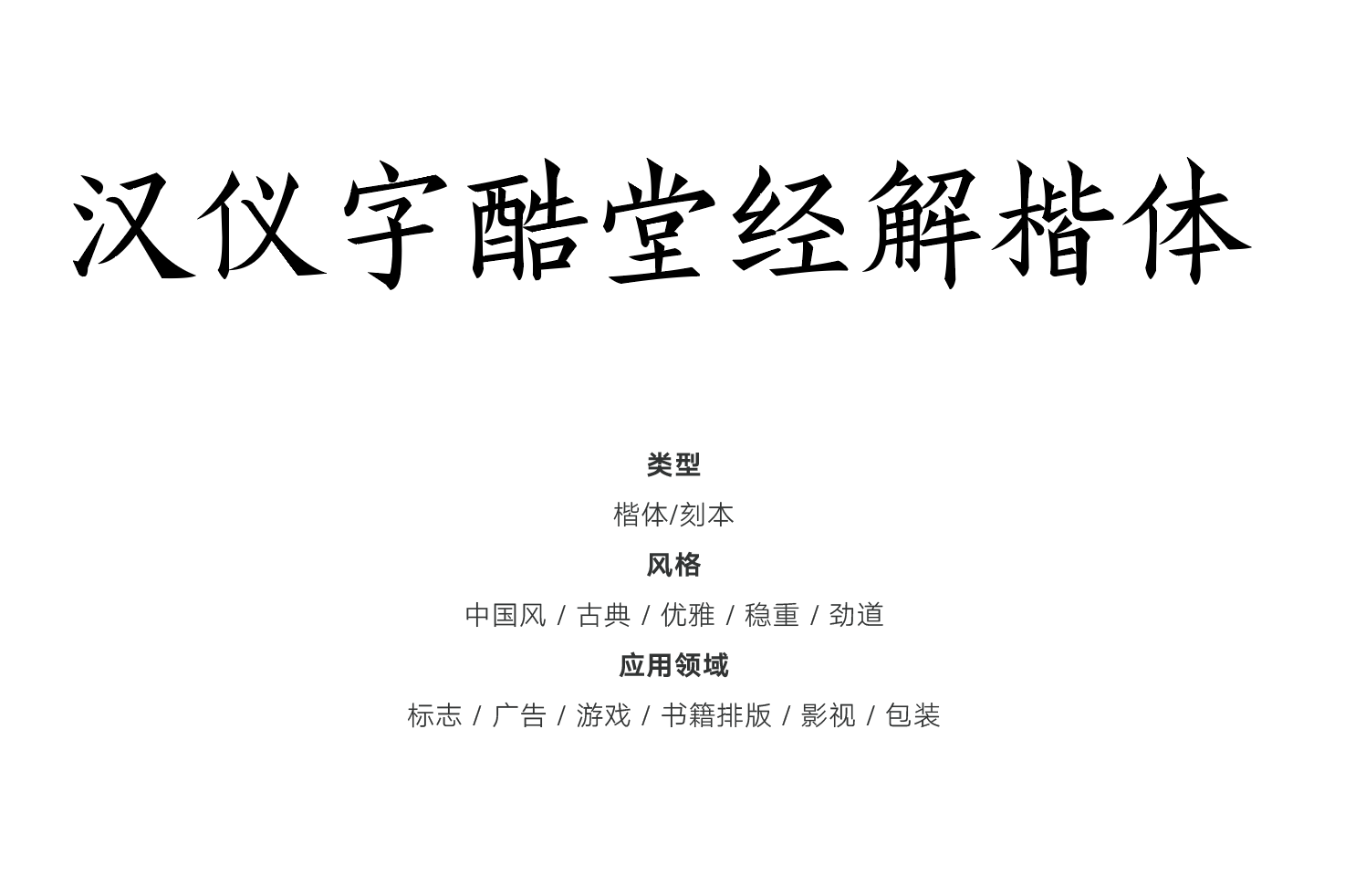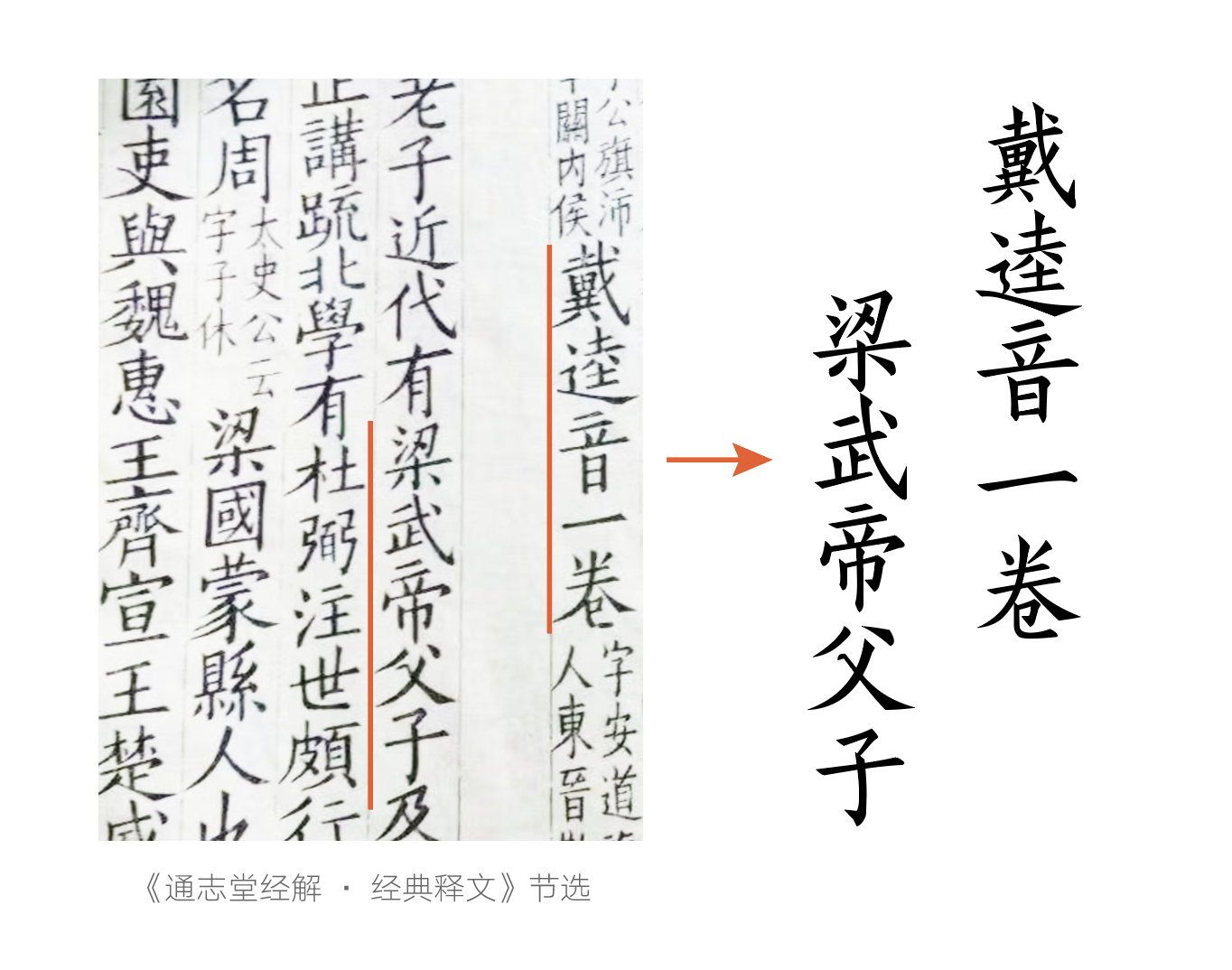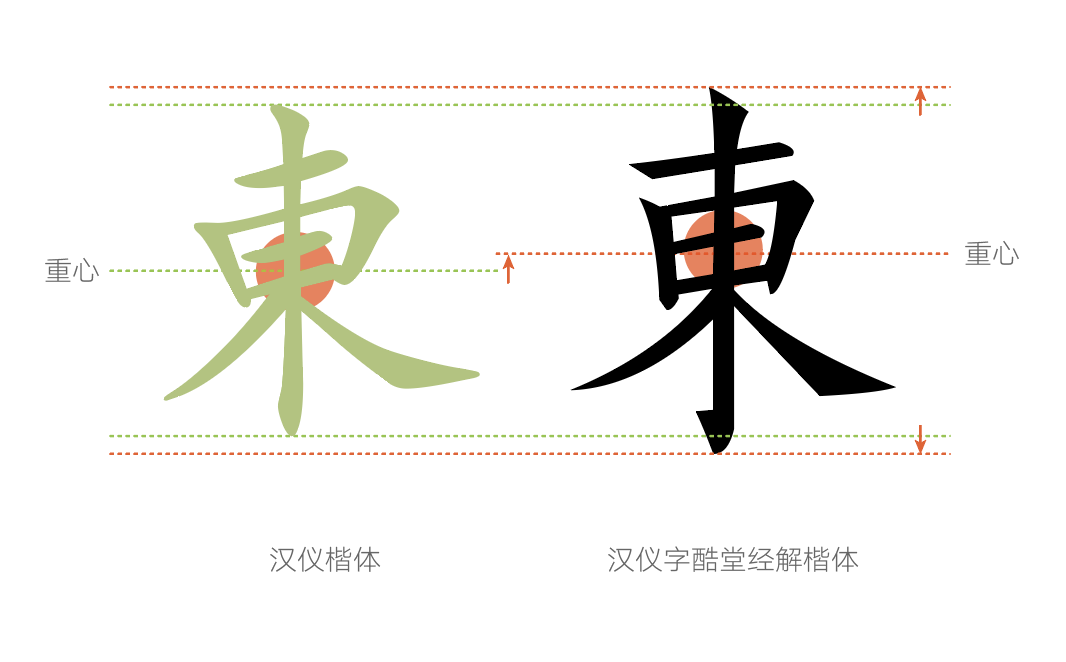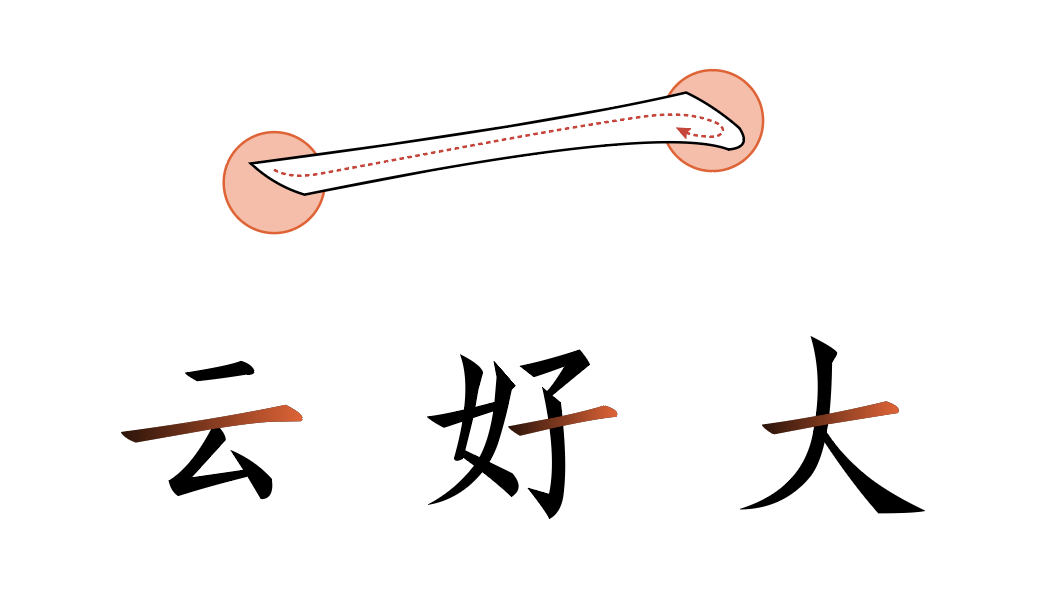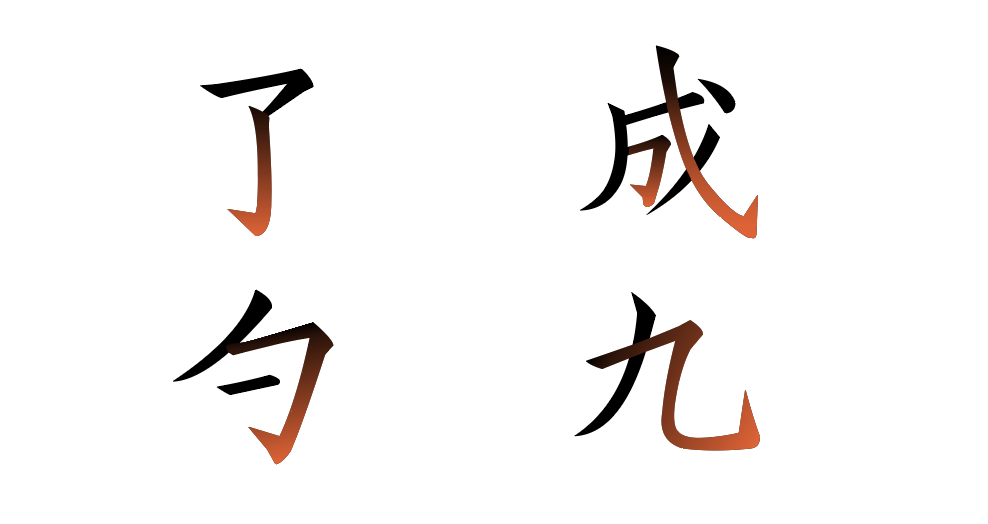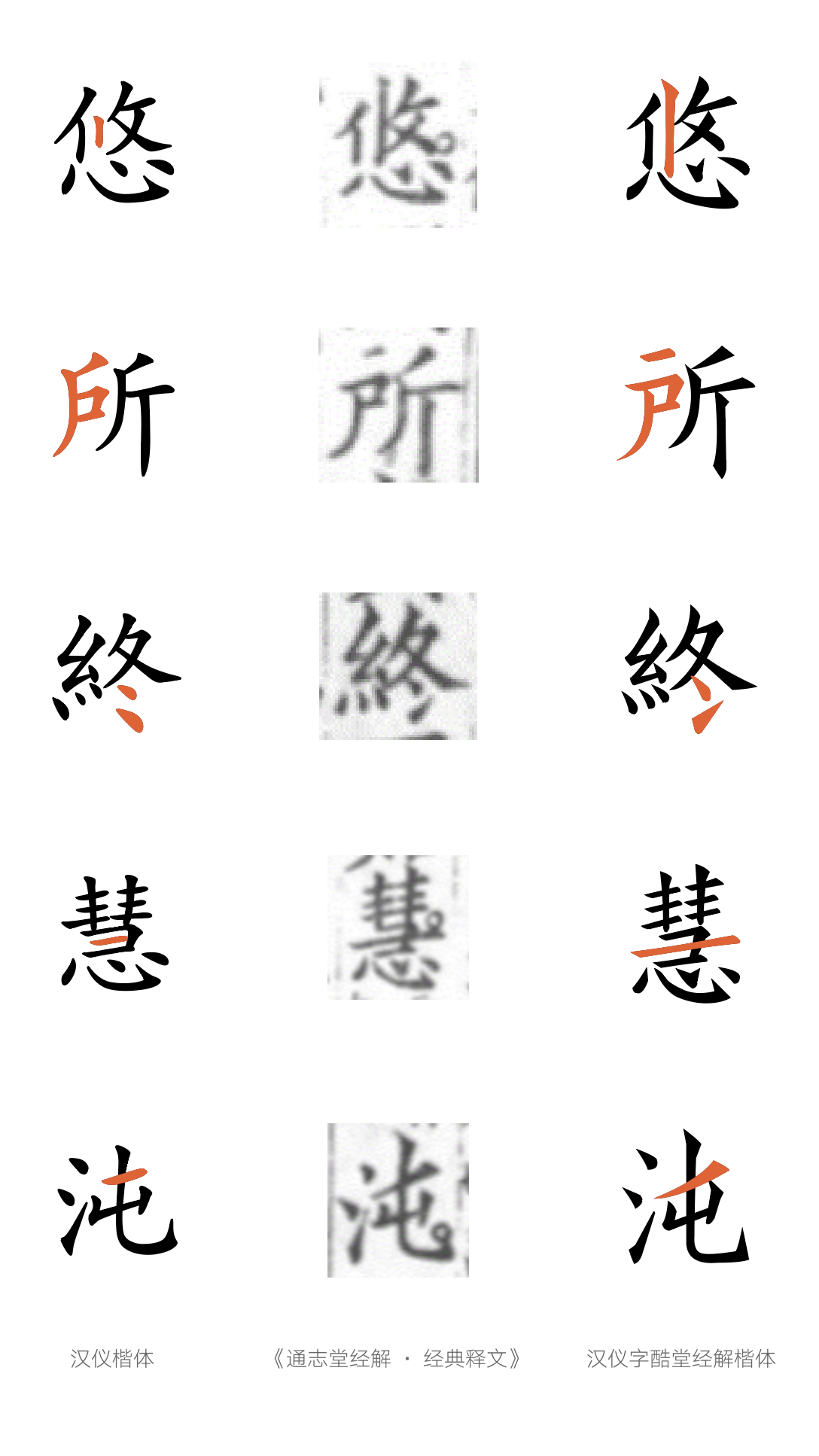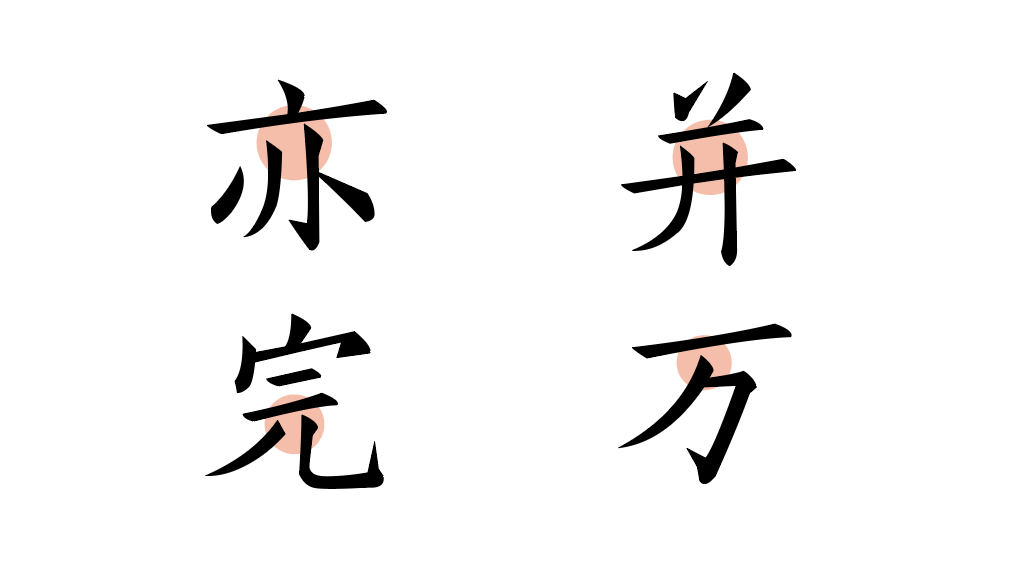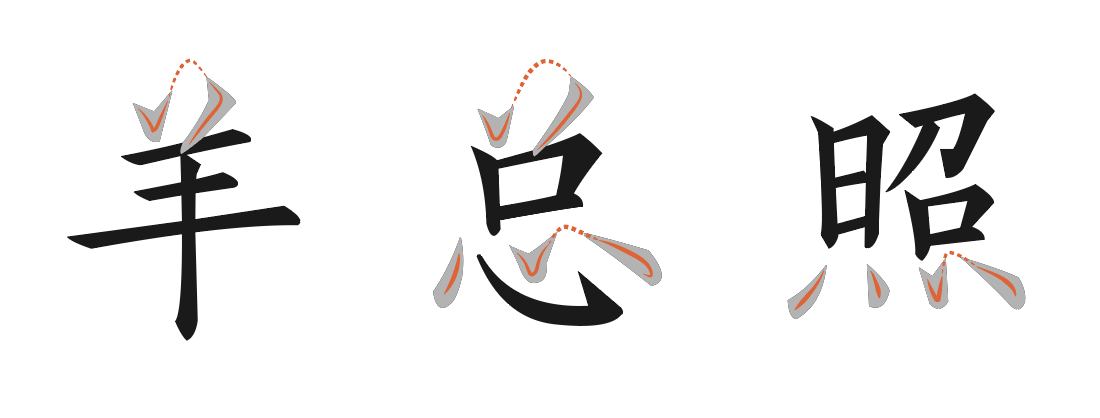
漢儀字酷堂經(jīng)解楷體
字體來(lái)源
漢儀字酷堂經(jīng)解楷體來(lái)源于古籍《通志堂經(jīng)解·經(jīng)典釋文》一書(shū)(清康熙年間,陸德明撰),字體有歐體楷書(shū)風(fēng)格,嚴(yán)謹(jǐn)工整、平正峭勁。
漢儀字酷堂經(jīng)解楷體作為一款復(fù)刻字體,保持了原刻本筆畫(huà)堅(jiān)挺,骨氣內(nèi)含,既不過(guò)分瘦勁,又不過(guò)分豐滿的風(fēng)格特點(diǎn),在貼近刻本原貌的同時(shí),還十分注重字符的易讀性和辨識(shí)性。
字形修長(zhǎng),嚴(yán)謹(jǐn)工整
相對(duì)于常見(jiàn)楷體(漢儀楷體)而言,漢儀字酷堂經(jīng)解楷體在縱向上的拉長(zhǎng)延伸使得字體在縱勢(shì)上顯得疏朗、修長(zhǎng)、剛勁、挺拔。
筆畫(huà)出鋒勁健,遒勁有力
漢儀字酷堂經(jīng)解楷體的筆畫(huà)方圓兼施,以方為主。橫畫(huà)左低右高,露鋒入筆,筆鋒尖銳,中部飽滿,收筆內(nèi)斂,形成一個(gè)圓弧頭。
漢儀字酷堂經(jīng)解楷體的點(diǎn)畫(huà)飽滿,活潑靈巧,筆勢(shì)連貫,點(diǎn)畫(huà)之間形斷意連,相互呼應(yīng)。
漢儀字酷堂經(jīng)解楷體的鉤畫(huà)像等腰三角形一樣,勁挺銳利,有“鐵畫(huà)銀鉤”之稱(chēng)。
漢儀字酷堂經(jīng)解楷體為了使字體更有呼吸感,氣息更加流暢,在部分上下結(jié)構(gòu)漢字的筆畫(huà)銜接處做了留白處理。
貼近刻本原貌
漢儀字酷堂經(jīng)解楷體遵從了傳統(tǒng)的書(shū)寫(xiě)方式,使其在布白均衡且易識(shí)別的前提下,最大程度還原了刻本的原貌。